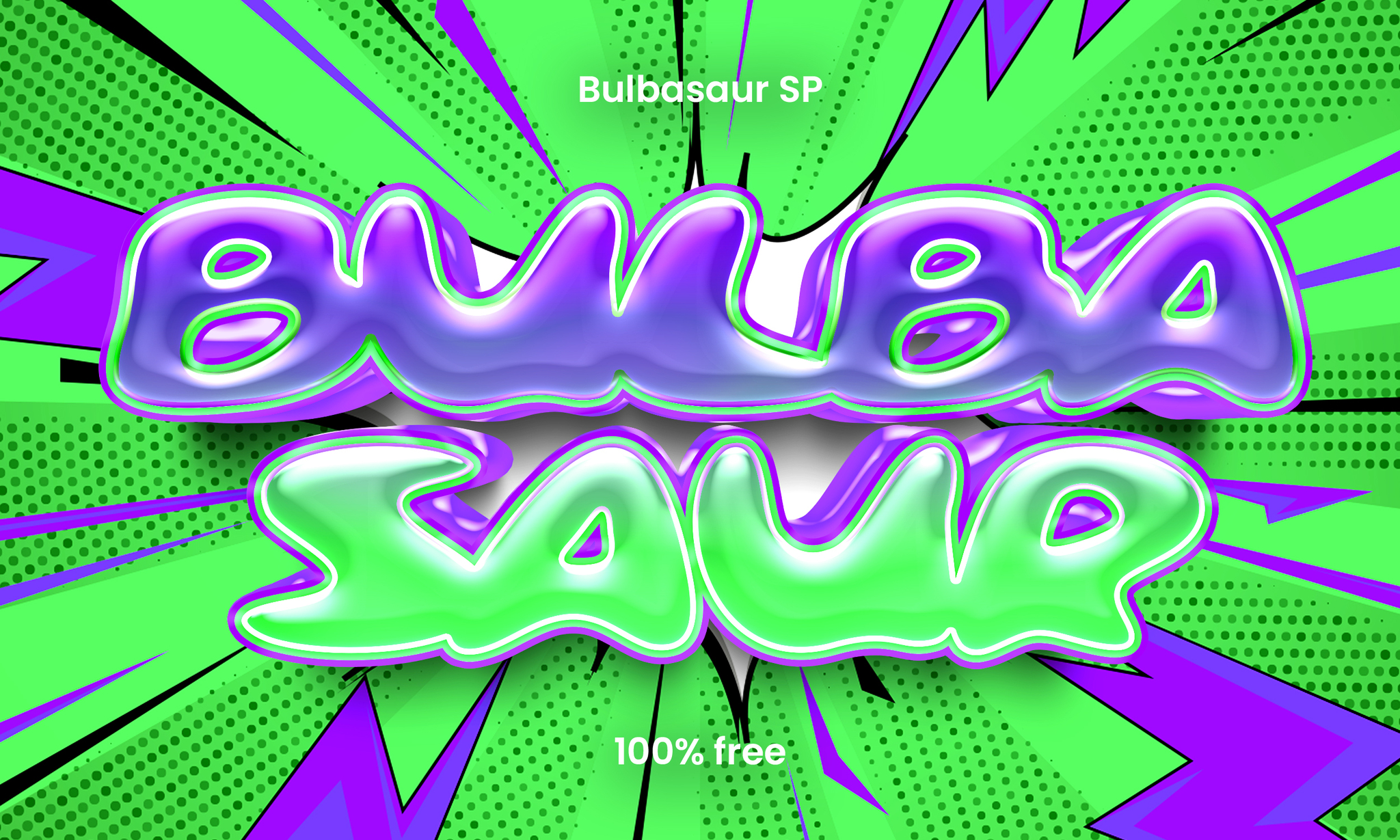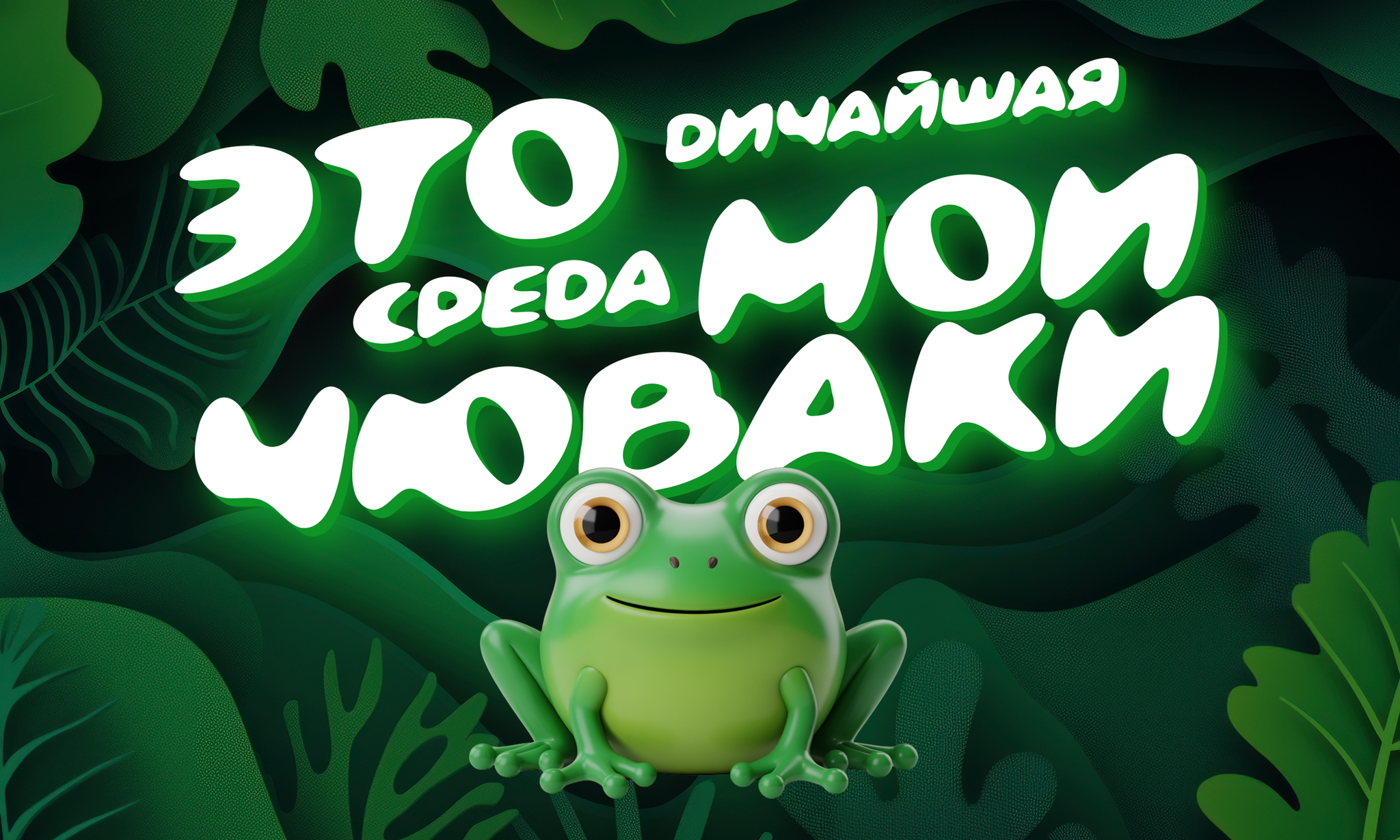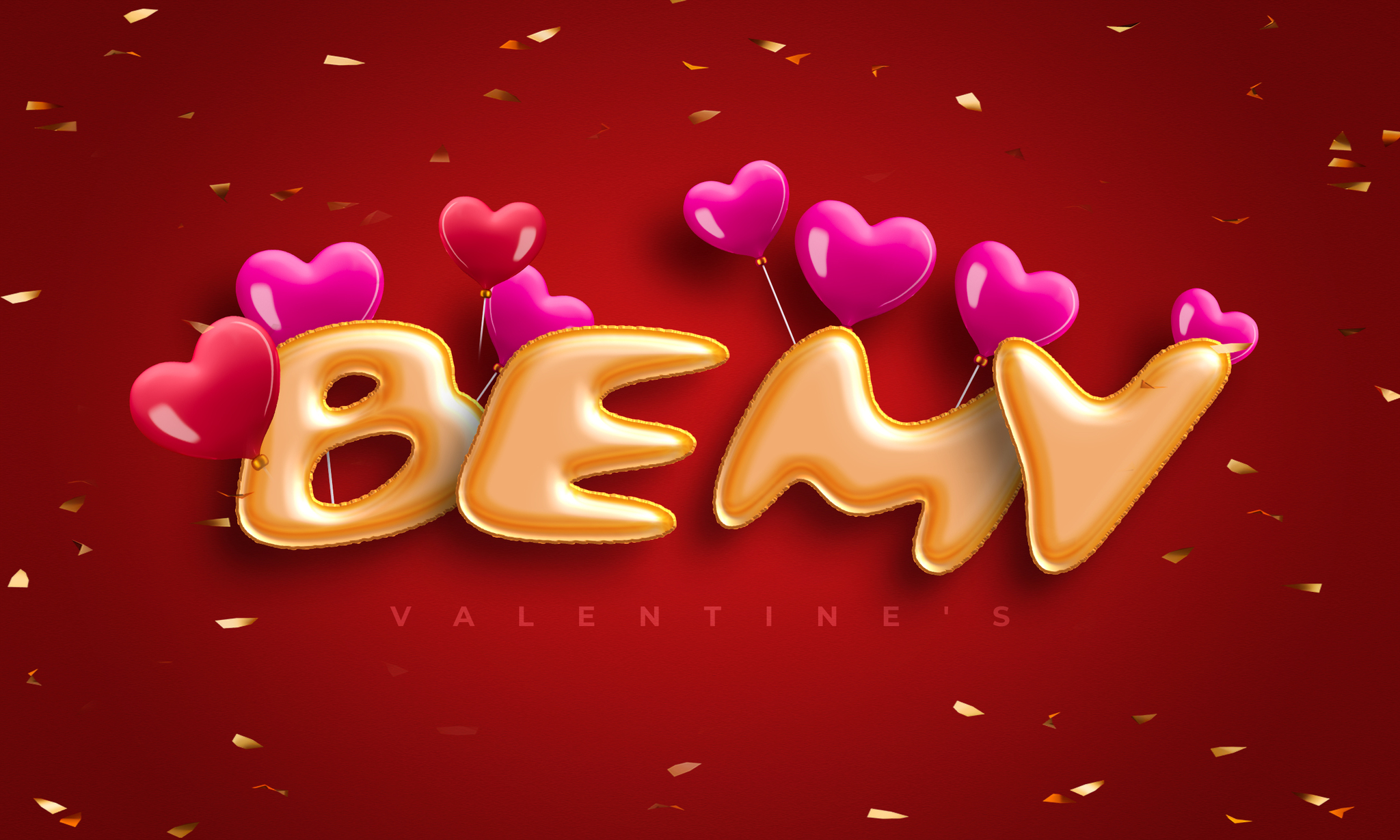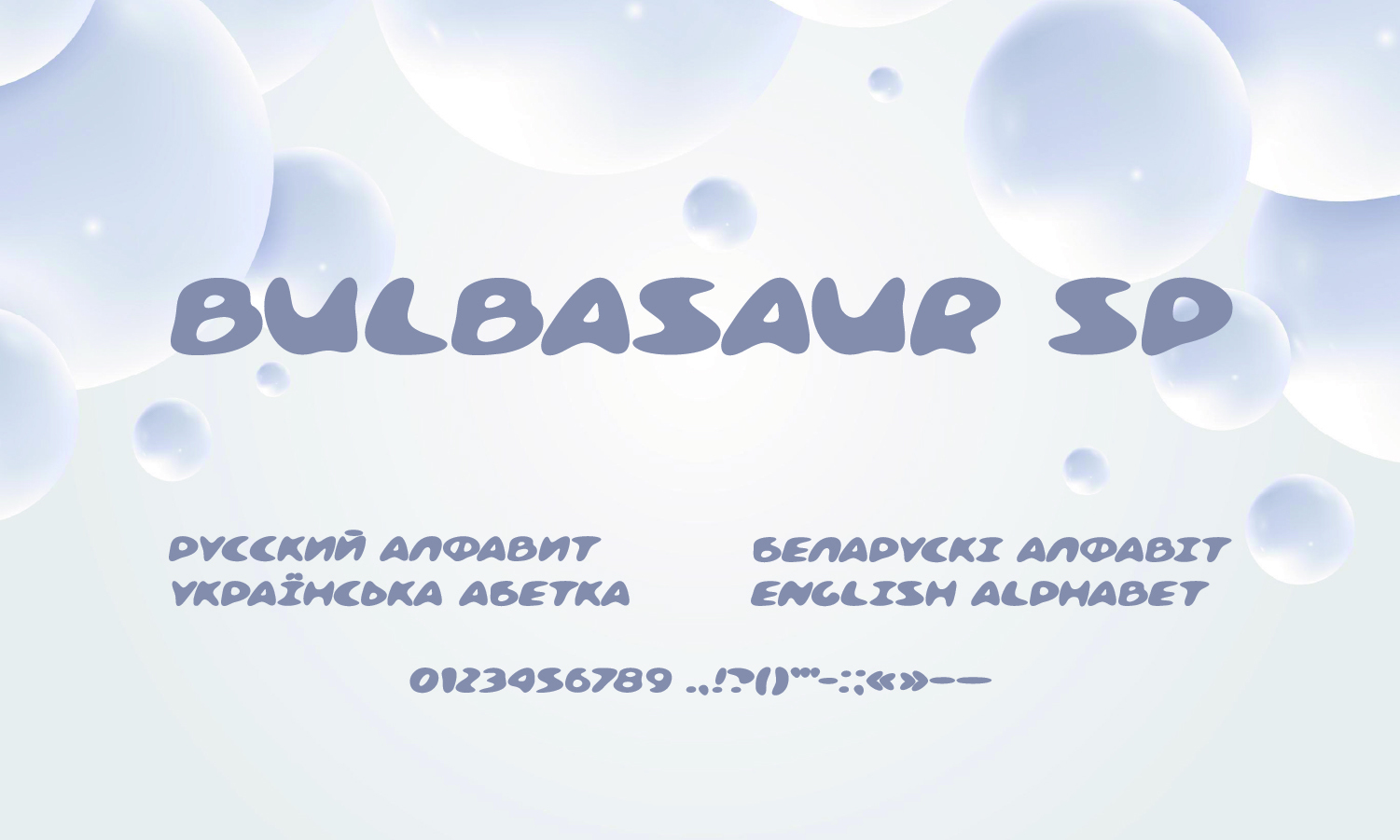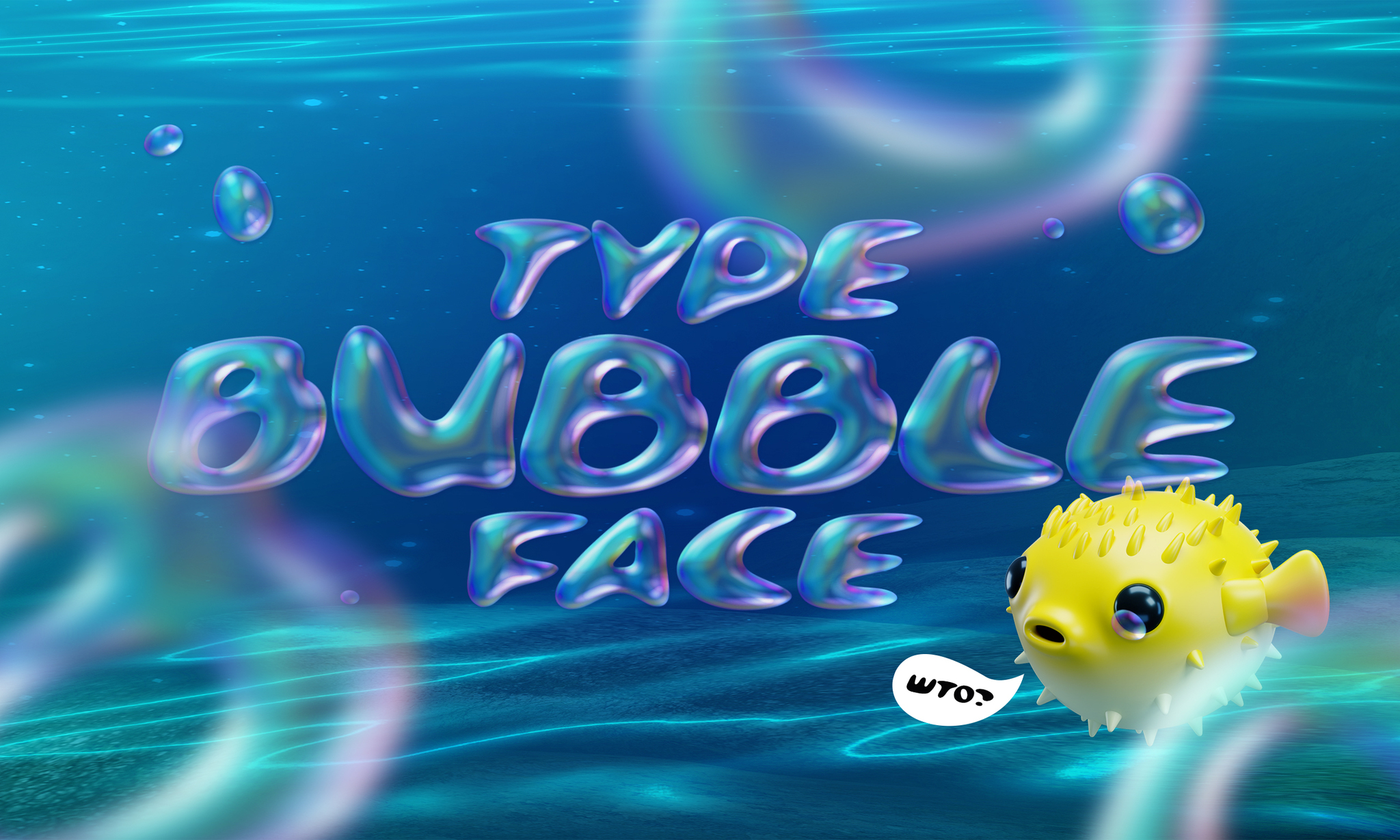
Бульбазавр SP — акцидентный шрифт с пухлыми округлыми буквами, отсылающий к формам известного покемона — Бульбазавра. Мягкая пластика делает строку дружелюбной, наивной и игривой.
Шрифт отлично смотрится в детских проектах, брендах сладостей и игрушек, обложках YouTube и афишах мероприятий.